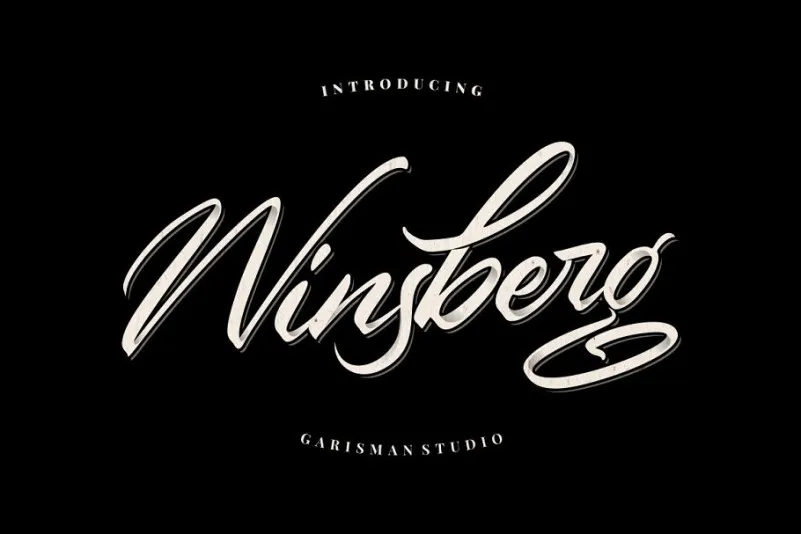
Winsberg Script Font – Download Grátis
A Winsberg Font é uma moderna escolha para aqueles buscando a fidelidade do estilo de escrita à mão. Este tipo de letra foi criado pelo Designer 0001themes, inspirado nas marcas e rasuras feitas às mãos, para capturar o realismo da escrita natural. A Winsberg está projetada especialmente para variedades de usos, desde embalagens até materiais publicitários. Seu estilo principal é perfeito para a adição de alternativas alfabéticas maiúsculas e conjuntos estilísticos complementares que se adaptam maravilhosamente aos diferentes formatos. Ideal tanto para logotipos quanto posters, etiquetas e materiais digitais, a Winsberg oferece um toque único para qualquer projeto. Ela é perfeita para tornar os seus projetos ainda mais atrativos em uma ampla gama de mídias, como cartazes, roupas personalizadas, frases sagradas, comunicados internos e tipografia.